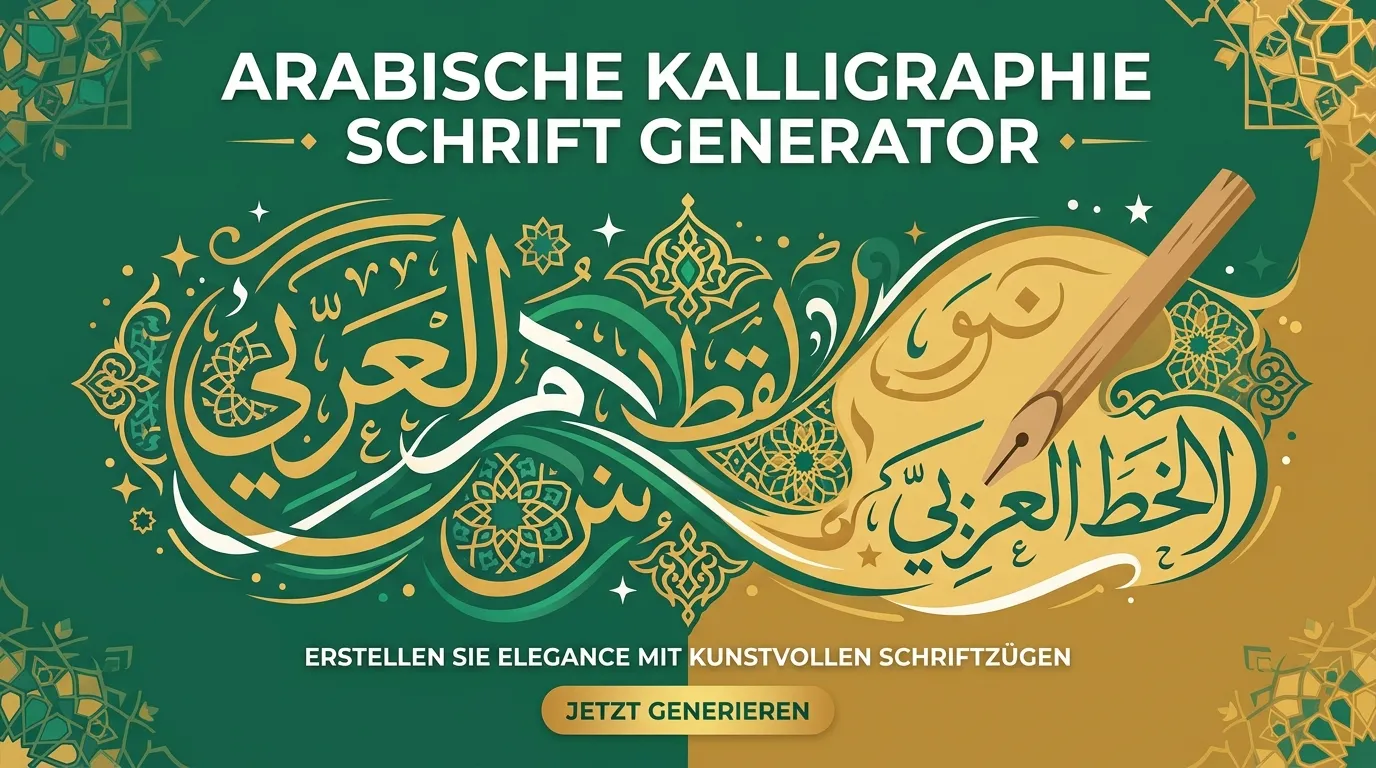
Arabische Kalligraphie Schrift Generator
Arabische Kalligraphie: Eine Jahrtausende alte Kunstform
Arabische Kalligraphie (al-khatt al-arabi) gehört zu den ältesten und einflussreichsten Schriftkünsten der Welt. Seit dem 7. Jahrhundert hat sie sich von einer reinen Schreibtechnik zur höchsten Kunstform im islamischen Kulturkreis entwickelt. Die UNESCO hat arabische Kalligraphie 2021 als immaterielles Kulturerbe der Menschheit anerkannt.
Die verschiedenen Stile: von der geometrischen Strenge des Kufi bis zur fließenden Eleganz des Diwani: spiegeln jeweils ihre historische Epoche und ihren Verwendungszweck wider. Kufi, der älteste Stil, wurde für die ersten Koran-Abschriften verwendet. Naskh, entwickelt im 10. Jahrhundert, ist heute die Standard-Druckschrift der arabischen Welt.
Arabisch-inspirierte Schrift für Social Media und Tattoos
Arabische Kalligraphie-Elemente sind in der westlichen Design-Welt zunehmend beliebt: von Tattoos über Wandkunst bis zu Social-Media-Bios. Dabei ist Respekt vor der Kulturbedeutung ebenso wichtig wie ästhetische Wirkung.
Wichtiger Hinweis: Unser Generator erzeugt Unicode-Texteffekte in arabisch-inspiriertem Stil. Für echte arabische Texte, insbesondere religiöse Zitate oder Namensgravuren, empfehlen wir immer eine Verifizierung durch einen Muttersprachler. Die Buchstabenverbindungen und diakritischen Zeichen (Harakat/Vokalzeichen) folgen komplexen Regeln, die bei maschineller Erzeugung fehlerhaft sein können.
Welche arabischen Kalligraphie-Stile gibt es?
Die fünf Hauptstile der arabischen Kalligraphie sind: Kufi (geometrisch, eckig, ältester Stil), Naskh (rund, gut lesbar, Standard für den Koran), Thuluth (geschwungen, ideal für Zitate und Poster), Diwani (elegant, verschnörkelt, aus der osmanischen Kanzlei) und Ruq'a (schnell, alltagstauglich). Jeder Stil hat eigene Regeln für Buchstabenverbindungen und Proportionen.
Ist die generierte arabische Schrift korrekt geschrieben?
Unser Generator erzeugt Unicode-Texteffekte, die arabisch-inspiriert aussehen. Für echte arabische Texte (z. B. Namen-Tattoos, religiöse Zitate) empfehlen wir dringend eine Verifizierung durch einen arabischen Muttersprachler, bevor du das Ergebnis für permanente Zwecke verwendest.
Kann ich arabische Kalligraphie für ein Tattoo verwenden?
Ja: als Inspiration und Vorschau. Falsch geschriebene arabische Tattoos sind ein bekanntes Problem (die Buchstaben verbinden sich unterschiedlich je nach Position im Wort). Lass jedes Tattoo-Design von einem Muttersprachler oder Kalligraphie-Experten prüfen, bevor du zum Tätowierer gehst.
Warum wird Arabisch von rechts nach links geschrieben?
Die arabische Schrift wird von rechts nach links (RTL) geschrieben: eine Konvention, die sich über Jahrhunderte aus älteren semitischen Schriften entwickelt hat. Die Buchstabenformen verändern sich je nach Position im Wort (Anfangs-, Mittel-, End- oder isolierte Form). Dieses System ermöglicht die fließenden Verbindungen, die arabische Kalligraphie so einzigartig machen.